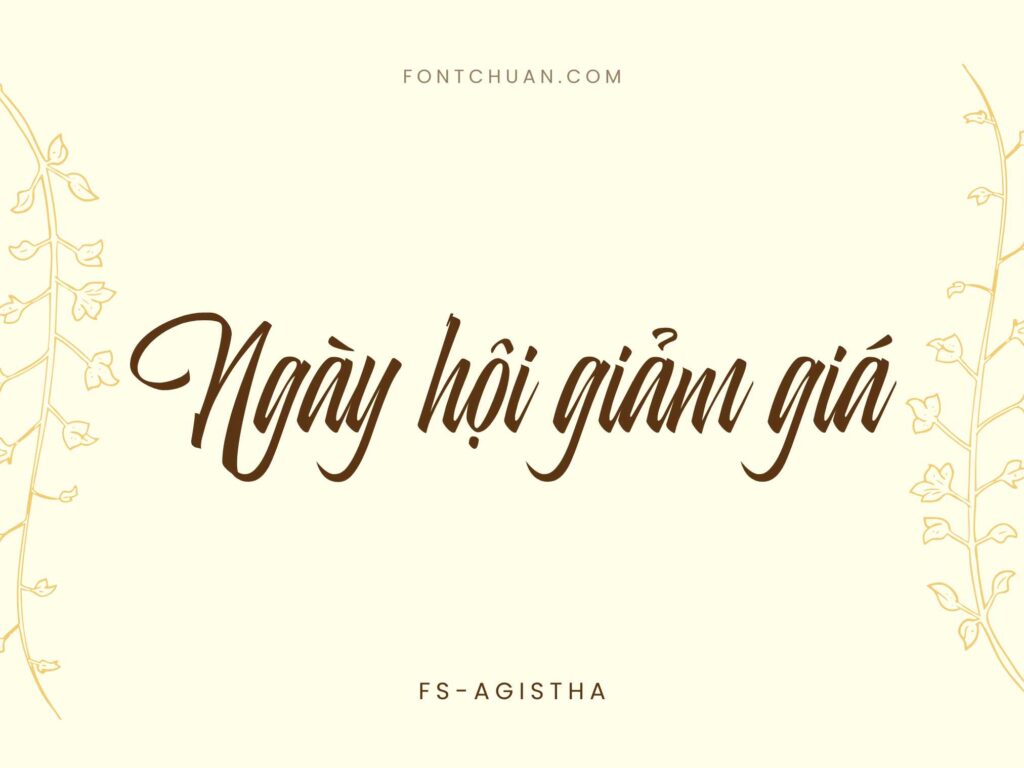
Font FS Agistha Logotype Việt Hóa
Agistha Script là một font chữ viết tay mềm mại, mang phong cách thanh lịch và hiện đại. Được thiết kế bởi Rotterlab Studio, font này nổi bật với các đường nét uyển chuyển, tạo nên sự duyên dáng và tinh tế trong từng ký tự. Với sự Việt hóa của Phông Chữ Việt, Agistha Script hỗ trợ đầy đủ các ký tự tiếng Việt, giúp người dùng dễ dàng áp dụng vào các thiết kế đa ngôn ngữ. Thành viên của Font Chuẩn đã sưu tầm và chia sẻ font này nhằm đáp ứng nhu cầu của cộng đồng thiết kế.
Về đặc điểm thiết kế, Agistha Script có các ký tự được vẽ tay tự nhiên, tạo cảm giác gần gũi và trang nhã. Font bao gồm đầy đủ chữ hoa, chữ thường, số và các ký tự đặc biệt, đồng thời hỗ trợ đa ngôn ngữ. Font này phù hợp cho các ứng dụng như thiệp mời, thiết kế logo, poster, bao bì sản phẩm và các ấn phẩm quảng cáo. Ngoài ra, Agistha Script cũng thích hợp cho các sự kiện đặc biệt như lễ hội, sinh nhật, Valentine và Trung thu, mang đến cảm giác ấm áp và sang trọng. Trong lĩnh vực ngành nghề, font này được ứng dụng rộng rãi trong quảng cáo, thiết kế thiệp cưới, giáo dục và công nghệ, giúp tăng tính thẩm mỹ và thu hút cho các sản phẩm và thương hiệu.